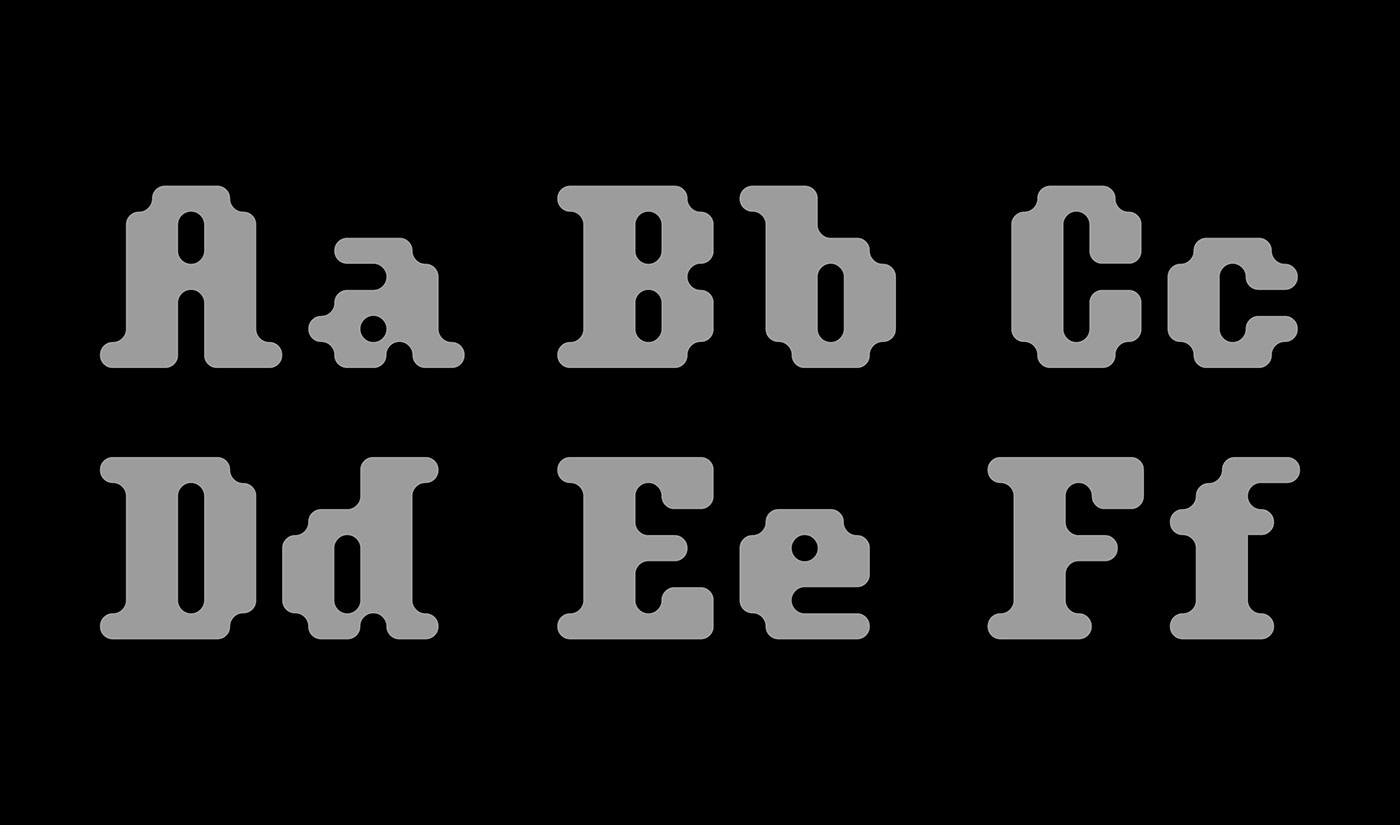
Tipografia Pixel Serifada Arredondada
[PT] Rotund é uma Tipografia Modular construída em um grid fixo e inspirada principalmente por fontes pixel display e em fontes bold gastas após usadas muitas e muitas vezes em impressões, incorporando curvas, charme e personalidade a essas fontes.
[ENG] Rotund is a Modular Typography built on a fixed grid and inspired mainly by pixel display fonts and bold fonts, worn after being used over and over again on printing, incorporating curves, charm and personality to these fonts.